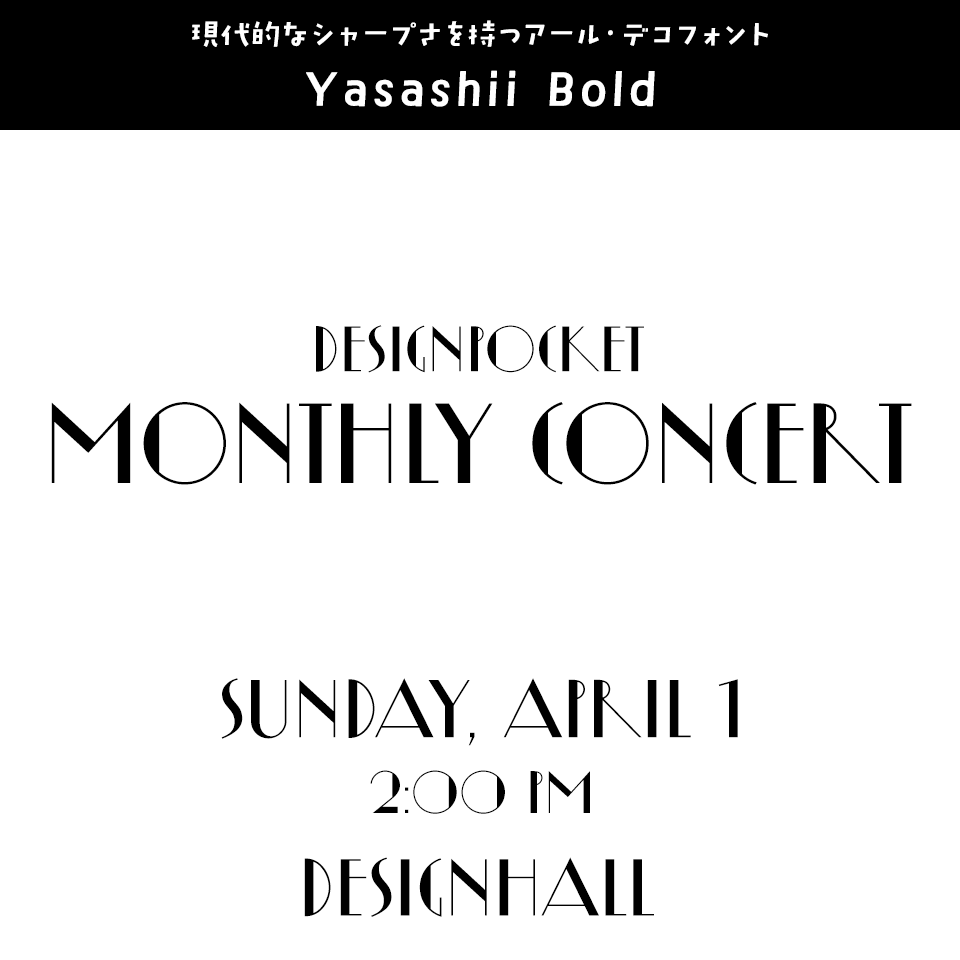
格調高い演奏会にシャープで古風な明朝体
KOさおとめ金陵M【欣喜堂】
和字書体さおとめMに、金陵『南齊書』(趙用賢・張一桂編、1589年、南京国子監)より再生した漢字、K.E.Taurus『ミラノ君主ヴィスコンティ家列伝』(1549年)より再生した欧字を追加した総合書体です。
レトロでオシャレな雰囲気のあるフォント
AR浪漫明朝体U【アーフィック】
大正浪漫を彷彿させる明朝系の書体です。太さもあるので見出し・タイトルに使いたいフォントです。
爽やかさがテーマのときにリアル手書き書体
空とひこうき【鈴木メモ】
空に長く伸びて行くひこうき雲をイメージした書体で、右上りの勢いとリアルな手書き感が特徴。写真やイラストに書き込みをしたように傾けたレイアウトで使用するのもおすすめです。
みんなたのしい発表会に合う手書き風書体
デコフォントおもちゃ書体【Design筆文字Font】
飛び跳ねているようなはらいやハネの丸みが、楽しく歌って踊る様子を想像させるたのしいフォントです。
音楽的特徴を持たせたデザイン書体
和音【REN FONT】
それぞれの字種に音楽的特徴を持たせ、文章として連なった時にメロディーのような彩りを演出します。合計9ウェイトを数学的アプローチで中間生成するという試みのもと制作された、まさに「和音=ハーモニー」の名にふさわしい仕上がりとなっています。
「音符の花」が特徴的なデザインフォント
タカ音花【タカ書体】
手書きフォント第9弾。音符をイメージさせる丸のエレメント。「音符の花」が賑やか咲き乱れ文字が踊り躍動的なリズムが弾ける。幾つかの丸の形をもち、ラインの頭や終わりに自在に配置した手書き書体。
こどもの演奏会にピッタリのかわいいフォント
パンダベーカリー【鈴木メモ】
手描きのような自然なリズム感と、見出しやパッケージにも最適なしっかりとした太さ。何より手作り感のある可愛らしさが特徴です。
音符をモチーフにしたインラインフォント
メロディライン【アトリエこたつ】
「メロディライン」は音符をモチーフにしたインラインフォントです。記号を入力して、音符に変換することができます。
現代的なシャープさを持つアール・デコフォント
Yasashii Bold【Dharma Type】
Yasashiiは、19世紀末から20世紀初頭にかけてのアール・デコスタイルのフォントです。特に日本の化粧品パッケージやポスターなどのシンプルなレタリングを参考に、レトロの雰囲気を残しつつ、現代的なシャープさを持つアール・デコフォントになっています。
ジャズやクラシックの演奏会に
Mt BloomScript Std【モトヤ】
ブラシで書いたようなカリグラフィーが特徴的な筆記体で、文章に躍動感を与えます。ジャズやクラシックなどの演奏会にハンサムな印象をプラスしたいときにどうぞ。